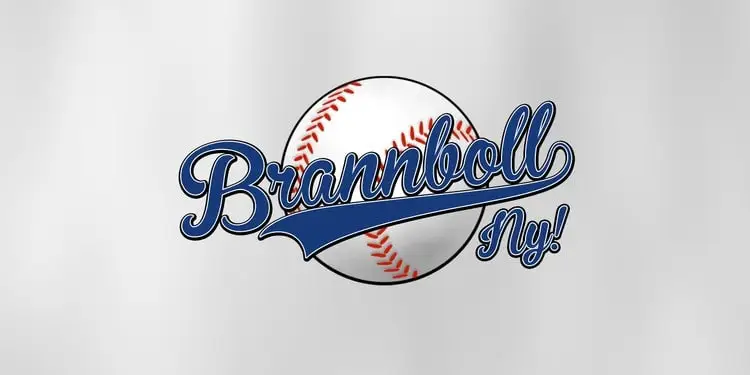
A Brannboll Ny Script é uma fonte script que traz ao seu design um toque nostálgico. Inspirada no estilo retro das letras e tipos dos anos 70 e 80, essa fonte oferece dois modos de uso: um com aparência limpa e robusta. Perfeita para aqueles que adoram uma dose do passado retrô em suas criações digitais, esta fonte contém dez swashes distintos para que você possa personalizar a aparência das palavras que escrever. É perfeitamente adequada para quem deseja dar um toque único aos textos em seus projetos, seja ele gráficos ou publicitários. Além disso, ela inclui números, o que expande ainda mais suas capacidades de uso. Sem dúvida, a Brannboll Ny Script é uma ótima escolha para quem busca trazer um ar vintage e criativo às suas criações digitais.